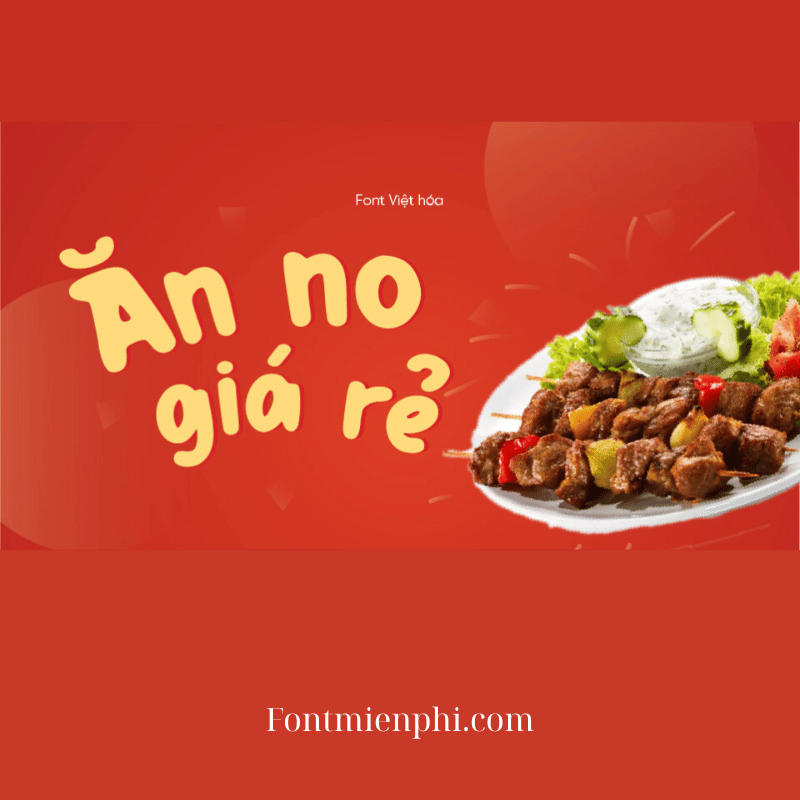
Font Việt hóa 1FTV VIP Red Burger
Font Việt Hóa 1FTV VIP Red Burger – Nét Chữ Độc Đáo, Sáng Tạo
Giới thiệu
Font Việt hóa 1FTV VIP Red Burger là một trong những phông chữ thiết kế độc đáo, mang phong cách trẻ trung và sáng tạo. Với kiểu chữ in đậm, góc cạnh kết hợp đường nét mềm mại, Red Burger phù hợp cho các dự án thiết kế poster, logo, banner hoặc nội dung quảng cáo ấn tượng. Font hỗ trợ đầy đủ bảng mã Tiếng Việt, giúp người dùng dễ dàng sử dụng trong mọi ấn phẩm truyền thông.
Đặc điểm nổi bật
• Thiết kế độc quyền: Phong cách chữ burger đậm, sắc nét, phù hợp với thiết kế nổi bật.
• Hỗ trợ Tiếng Việt: Tương thích Unicode, đầy đủ dấu, không lỗi font khi sử dụng.
• Đa dạng ứng dụng: Dùng cho in ấn, quảng cáo, social media, game, và nhiều lĩnh vực sáng tạo khác.
Kết luận
Font Việt hóa 1FTV VIP Red Burger là lựa chọn lý tưởng cho các designer muốn tạo điểm nhấn trong tác phẩm của mình. Với phong cách trẻ trung và khả năng tương thích Tiếng Việt hoàn hảo, đây chắc chắn là font chữ không thể bỏ qua trong bộ sưu tập của bạn!